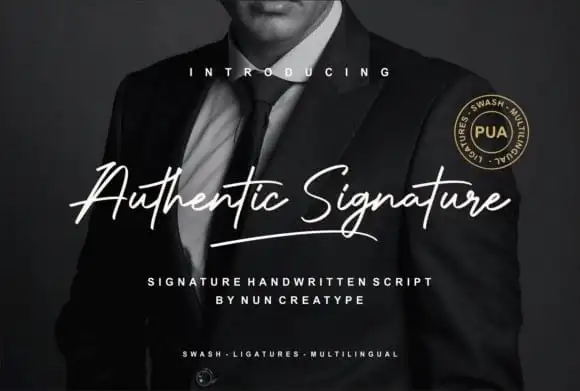
Authentic – Signature Script Font – Download Grátis
A Authentic é uma nova fonte de traço autêntico criada pela Nun Creatype com um design de forma suave e estilo de caligrafia luxuoso, perfeita para projetos de marca, logomarcas, designs de casamentos, postagens nas redes sociais, anúncios, embalagens de produtos, desenhos dos produtos, etiquetas, fotografia, marcadores de impressão, convites e assinaturas. Esta fonte traz uma sensação de escrita realista para seu próximo projeto, seja um design minimalista ou algo mais elaborado e sofisticado. A Authentic é perfeita para aqueles que desejam dar um toque autêntico e elegante a suas criações digitais.